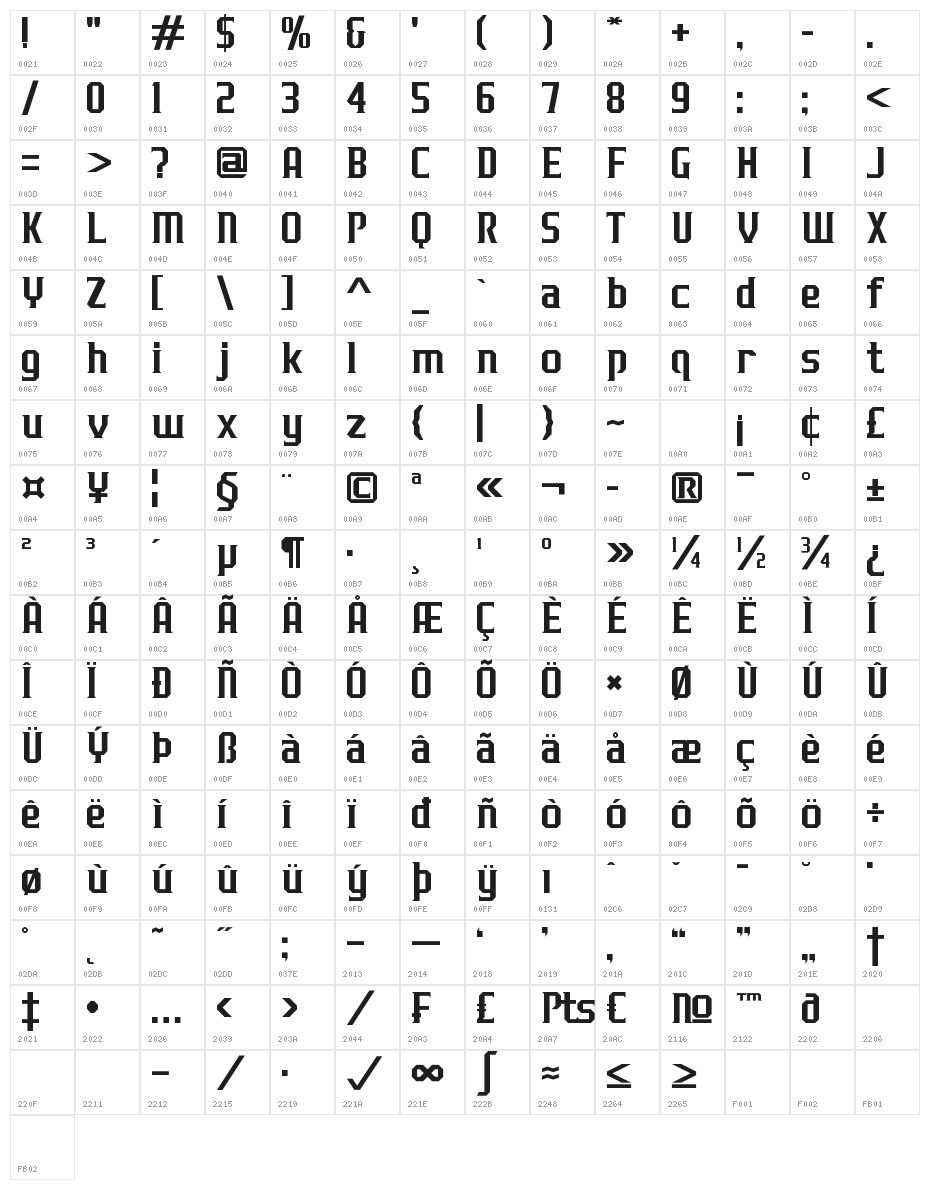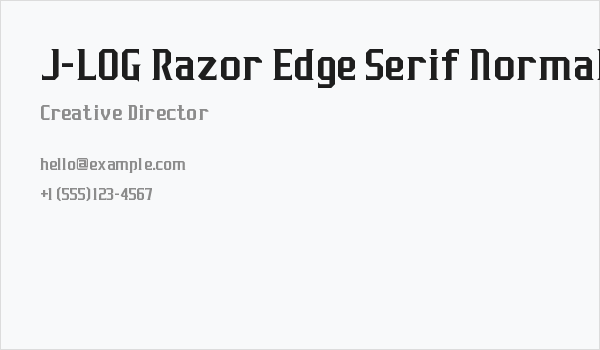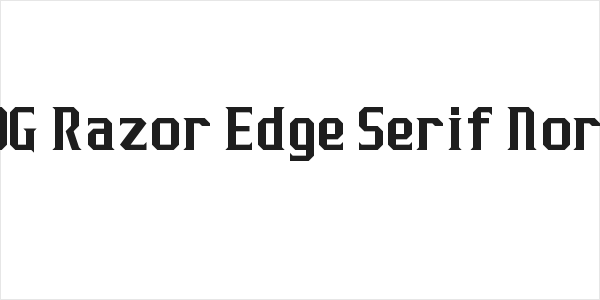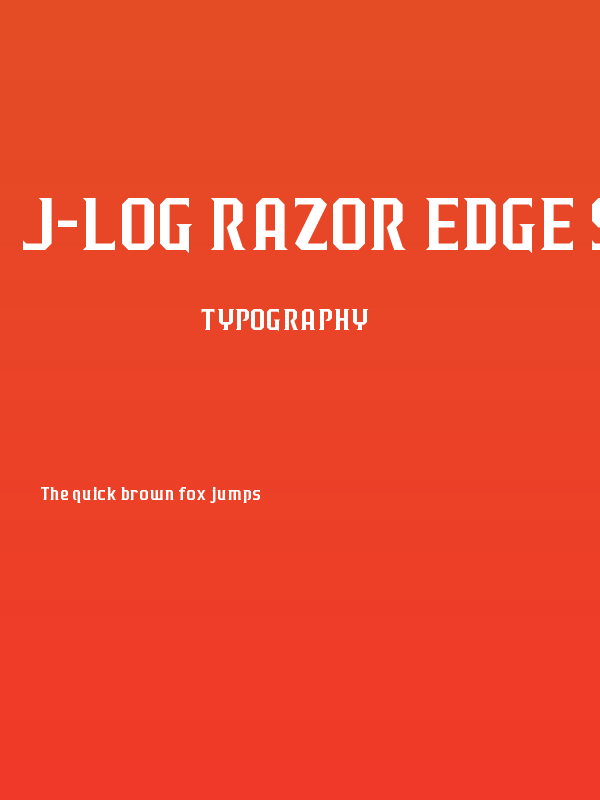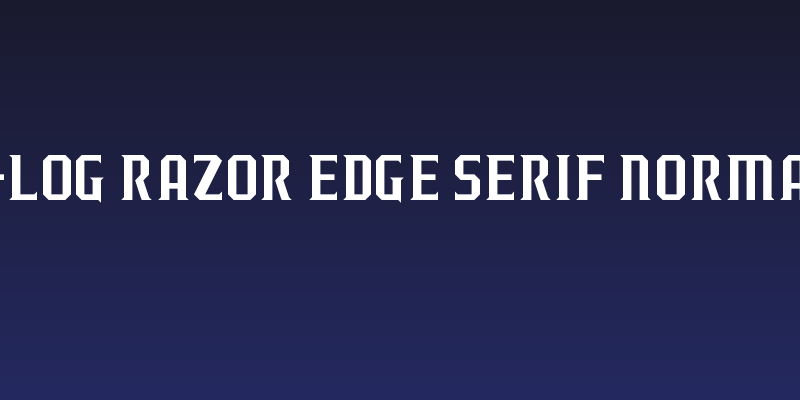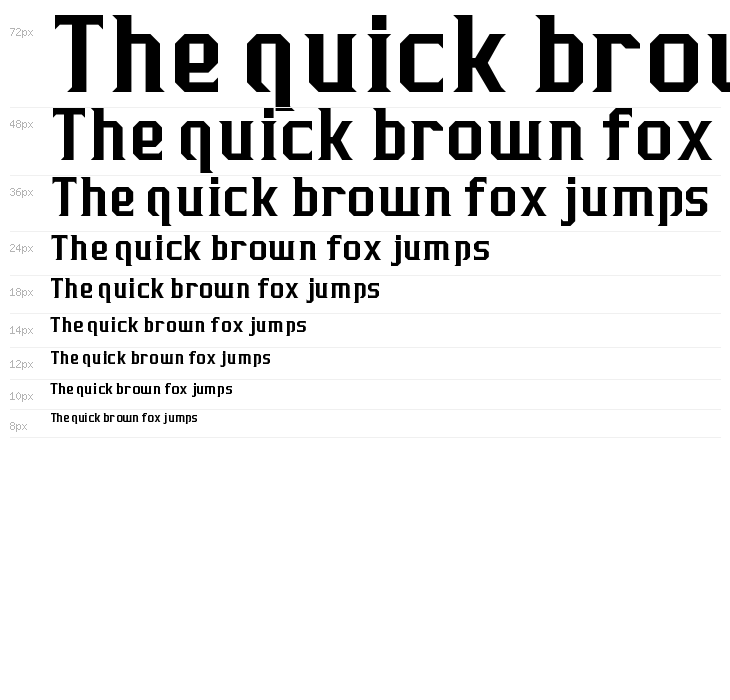
J-LOG Razor Edge Serif Normal Font
| Categorie | Serif |
| Progetti proposti | Ideal for branding, poster design, and headlines that require a strong visual impact. |